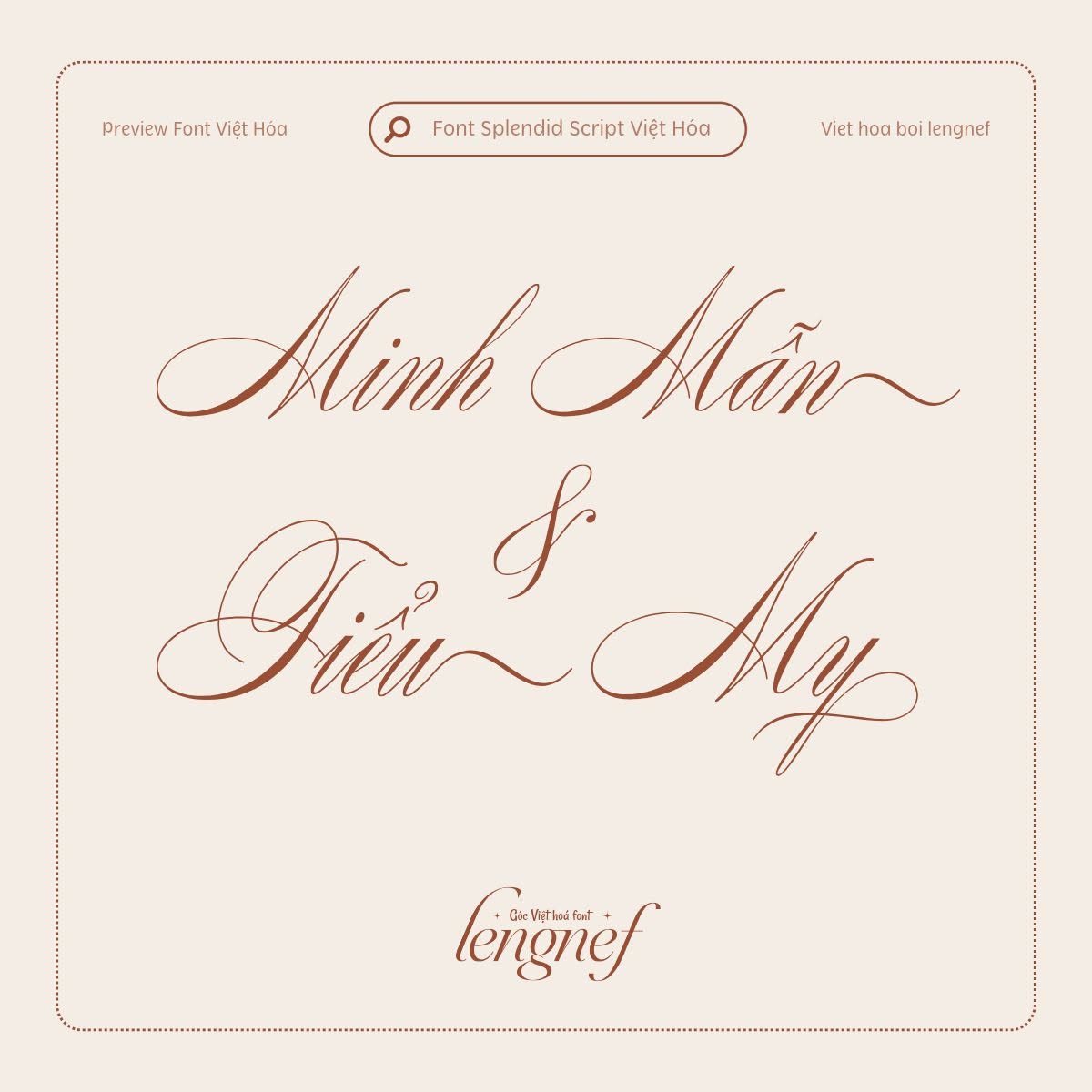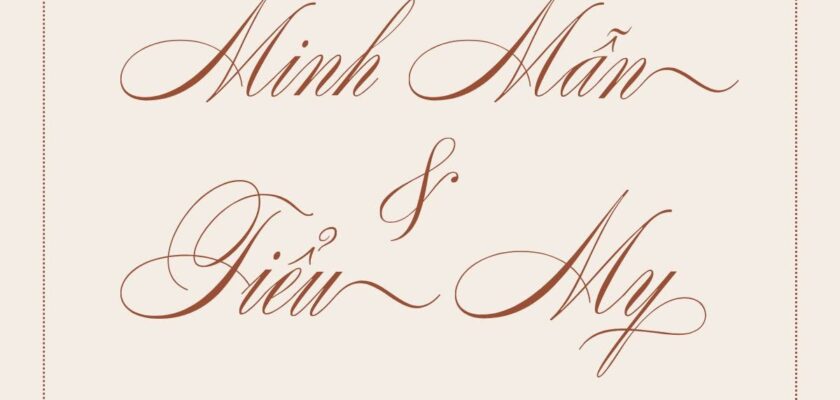
- Tác giả: Storm Type Foundry
- Việt hóa: lengnef
Splendid Script là phông chữ viết tay cổ điển nằm trong bộ Splendid Quartett của Storm Type, được thêm vài kiểu glyph làm cho nó phù hợp với các thiết kế sang trọng, thiệp cưới, chúc mừng…